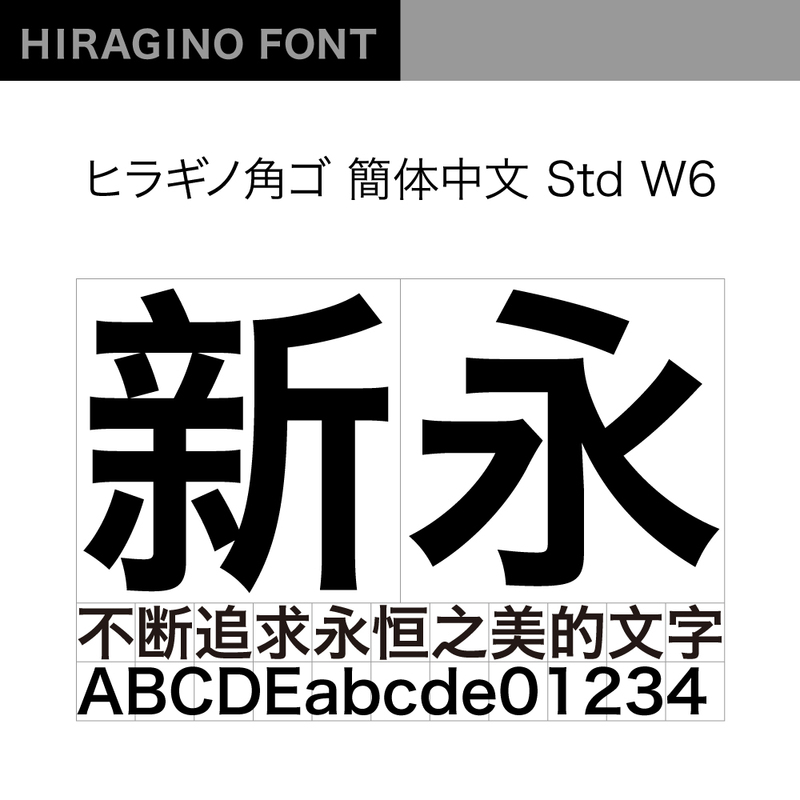
【ヒラギノ角ゴ 簡体中文 Std】中国国内で広く普及している文字セットのGB2312-80に対応した中国語フォント。企業のVIやCIにおける制定書体(コーポレートフォント)やWebサイト、案内サインなど、日本語と組み合わせて使用いただくことで、統一感のある多言語表記・ブランディングを実現。もちろん、「ヒラギノ角ゴ 簡体中文 Std」単体で使用しても、美しく読みやすいデザインに仕上がります。